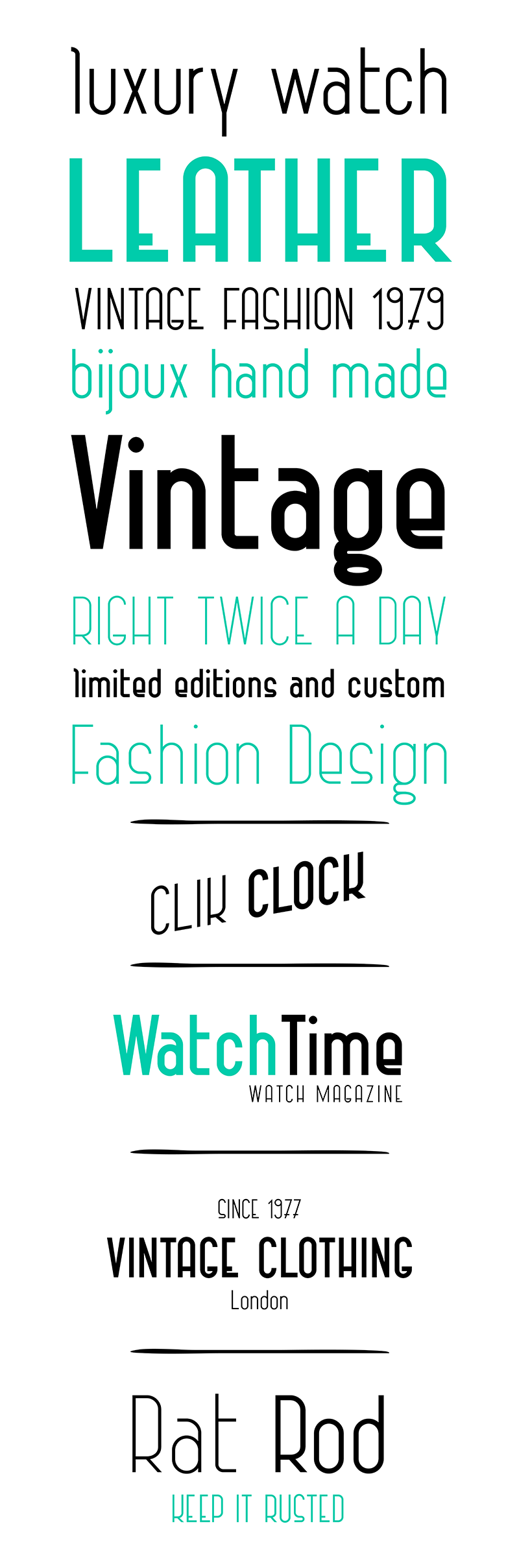
A Vintage Straps Font Family é uma ótima escolha para quem busca um estilo clássico moderno. Criada para representar os adoráveis elásticos vintage, essa fonte tem sua inspiração nas estilosas solenhas dos primeiros anos do século XX. A ideia era transmitir aquele charmoso toque nostálgico sem perder o brilho atual. O processo de criação envolveu a mistura de um tipo geométrico moderno, com linhas que se curvam e alongadas para simular o estilo tipográfico da década passada. O resultado é uma fonte ideal para usar em notícias, newsletters, panos de fundo publicitários ou até mesmo grandes outdoors. Com essa fonte na sua estante, você pode trazer um ar aconchegante e autêntico ao seu design com aparência clássica. É perfeita para quando precisamos transmitir uma mensagem clara, mas com um toque único de personalidade – seja em um editorial de jornal ou em anúncios de rua. Seja você, o designer criativo, ou a agência publicitária, esta fonte traz elegância e identidade ao seu trabalho, especialmente quando combinada para criar uma composição arquitetônica irresistivelmente bonita.